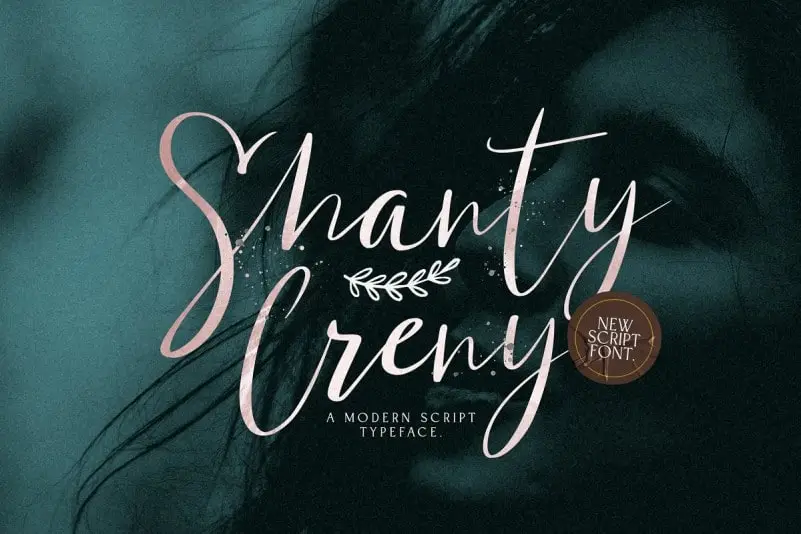
Shanti Creny Script Font – Download Grátis
A Shanti Creny Script Font é uma nova opção para quem busca adicionar elegância e luxo aos seus projetos digitais. Feita para designers que desejam dar um toque moderno a qualquer layout, esta fonte vem revolucionando o mundo das gráficas no Brasil. Seja em criações de marca, cabeçalhos, designs para casamentos, cartões de convite, assinaturas ou logos, ela traz uma versatilidade que se destaca. Esta fonte moderna é perfeita para quem procura algo mais além do padrão tradicional. Ela eleva os projetos a um nível superior, proporcionando um toque sofisticado sem perder a simplicidade elegante dos designs manuscritos. Seja para criar uma identidade de marca única e memorável ou para personalizar cartões de convite e selos, a Shanti Creny Script Font oferece um diferencial em cada projeto. Sem dúvida, esta fonte é uma escolha inteligente para quem busca uma mistura perfeita entre a elegância tradicional dos textos manuscritos e a modernidade do design digital. Uma vez que ela pode ser aplicada a uma ampla gama de projetos gráficos, vale a pena experimentar a Shanti Creny Script Font para enriquecer qualquer layout.